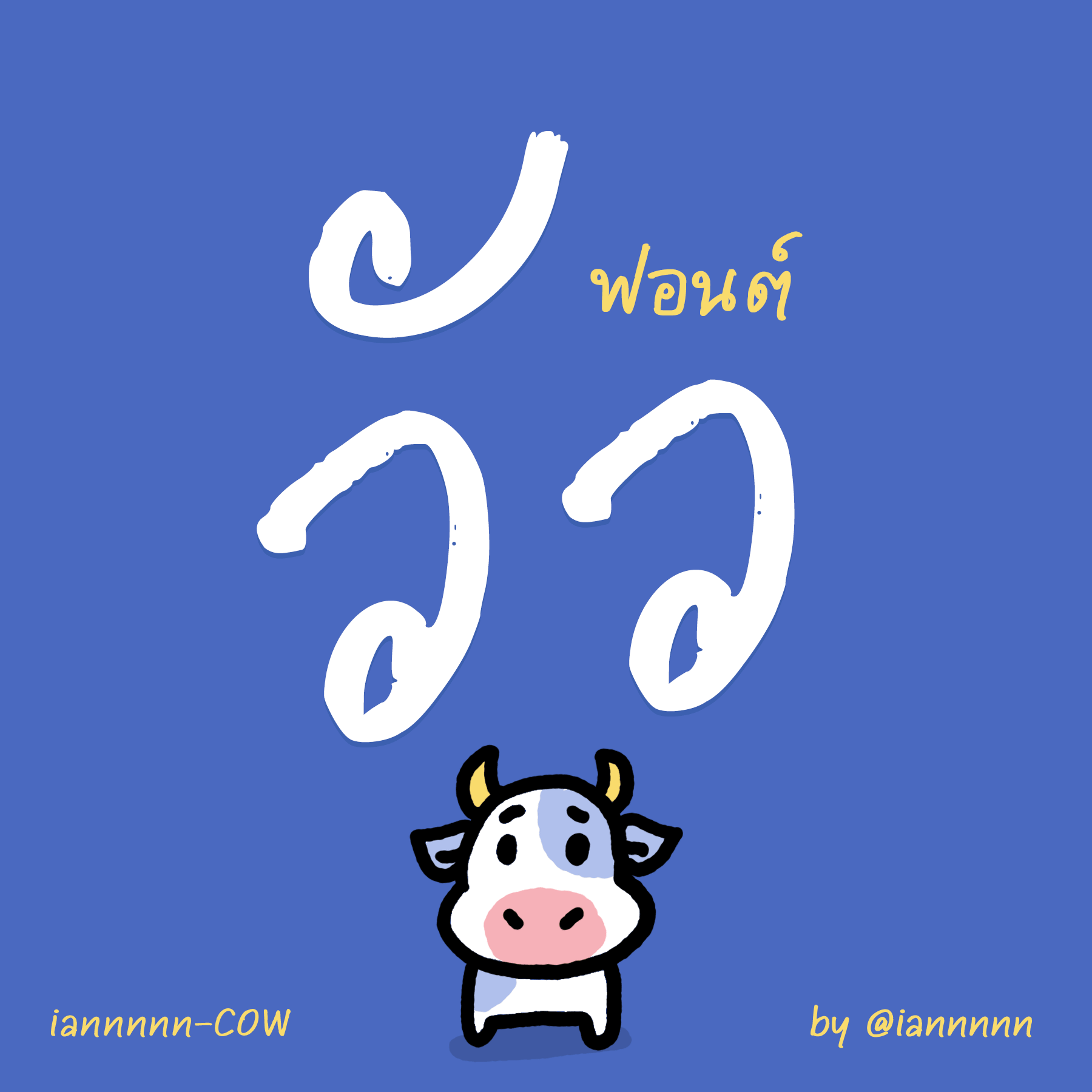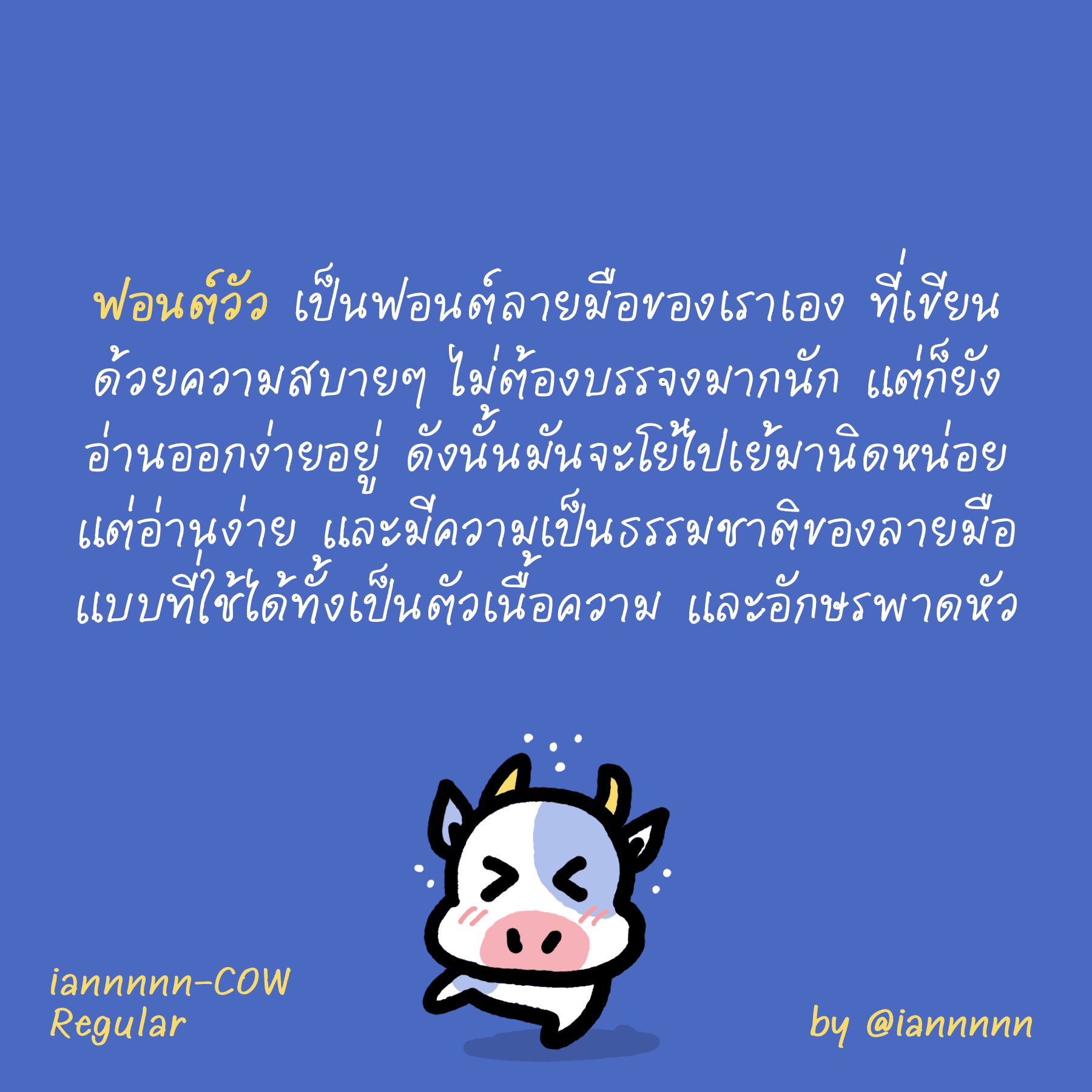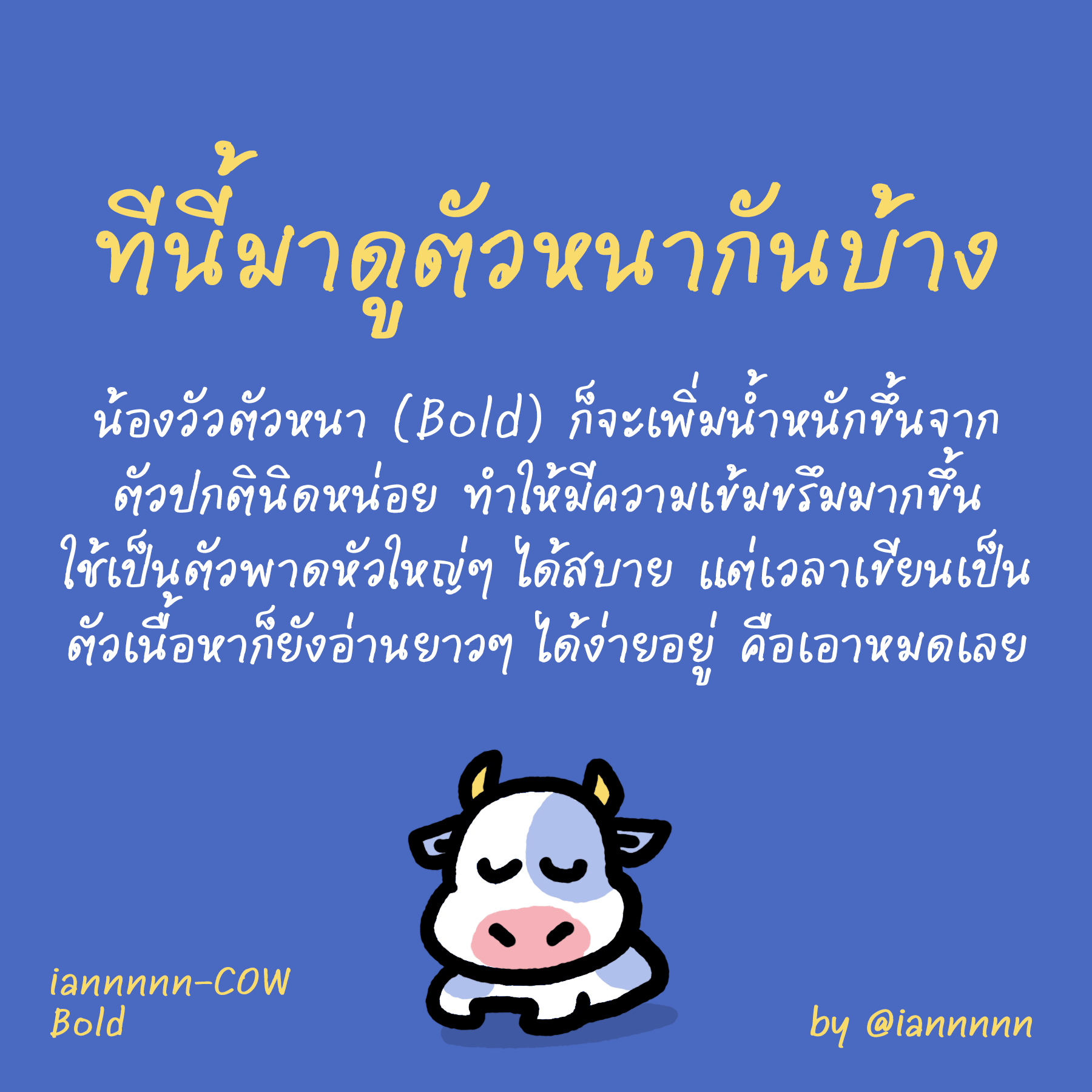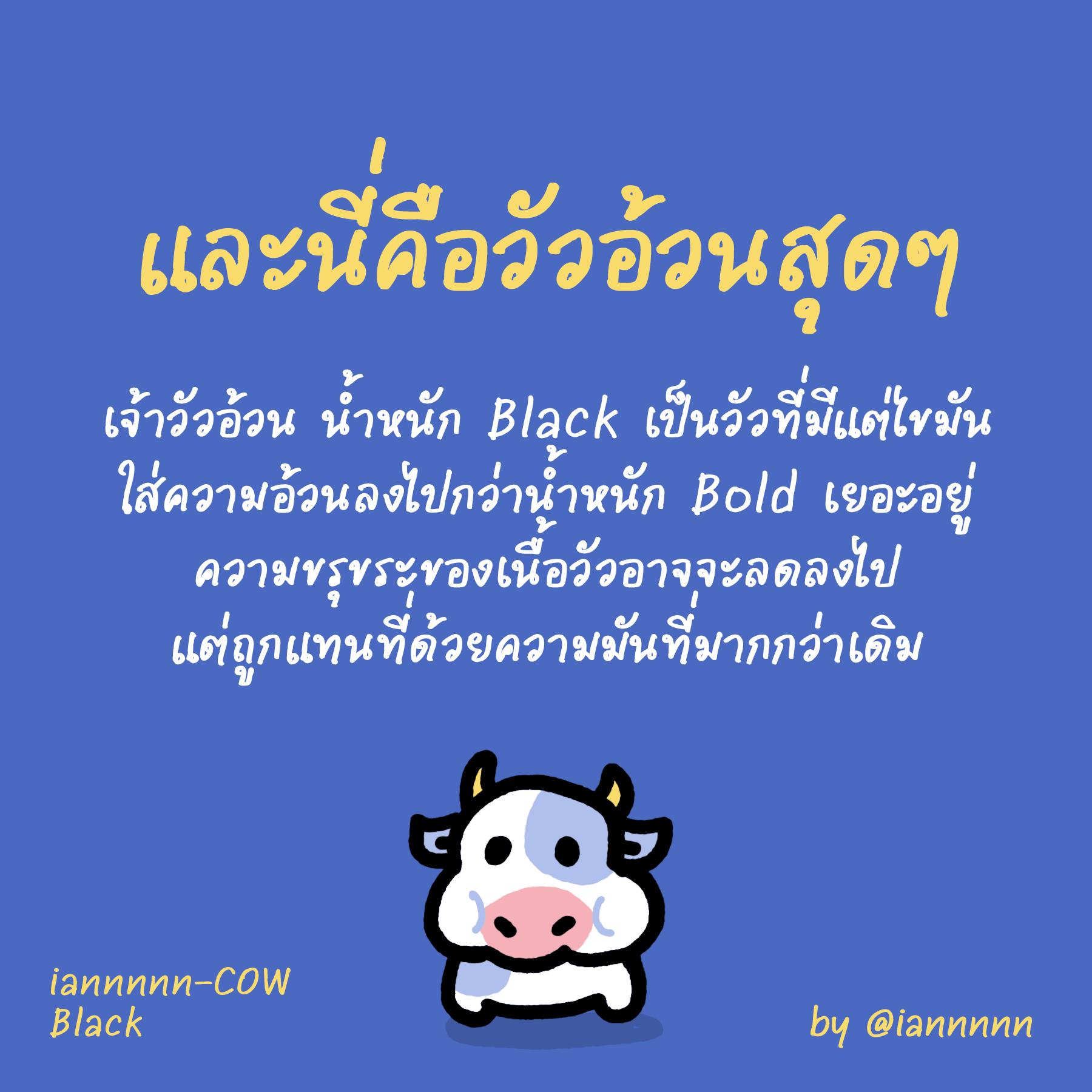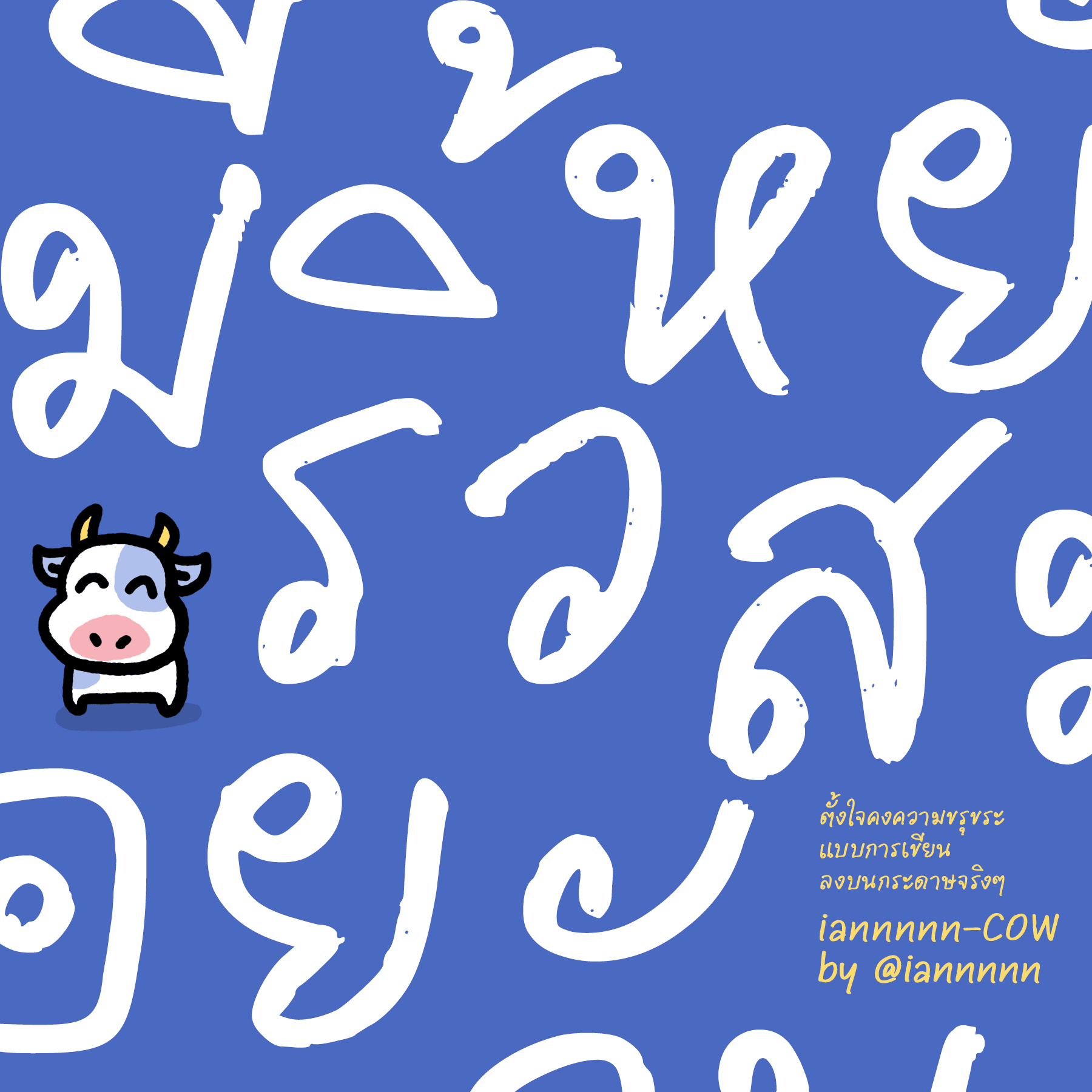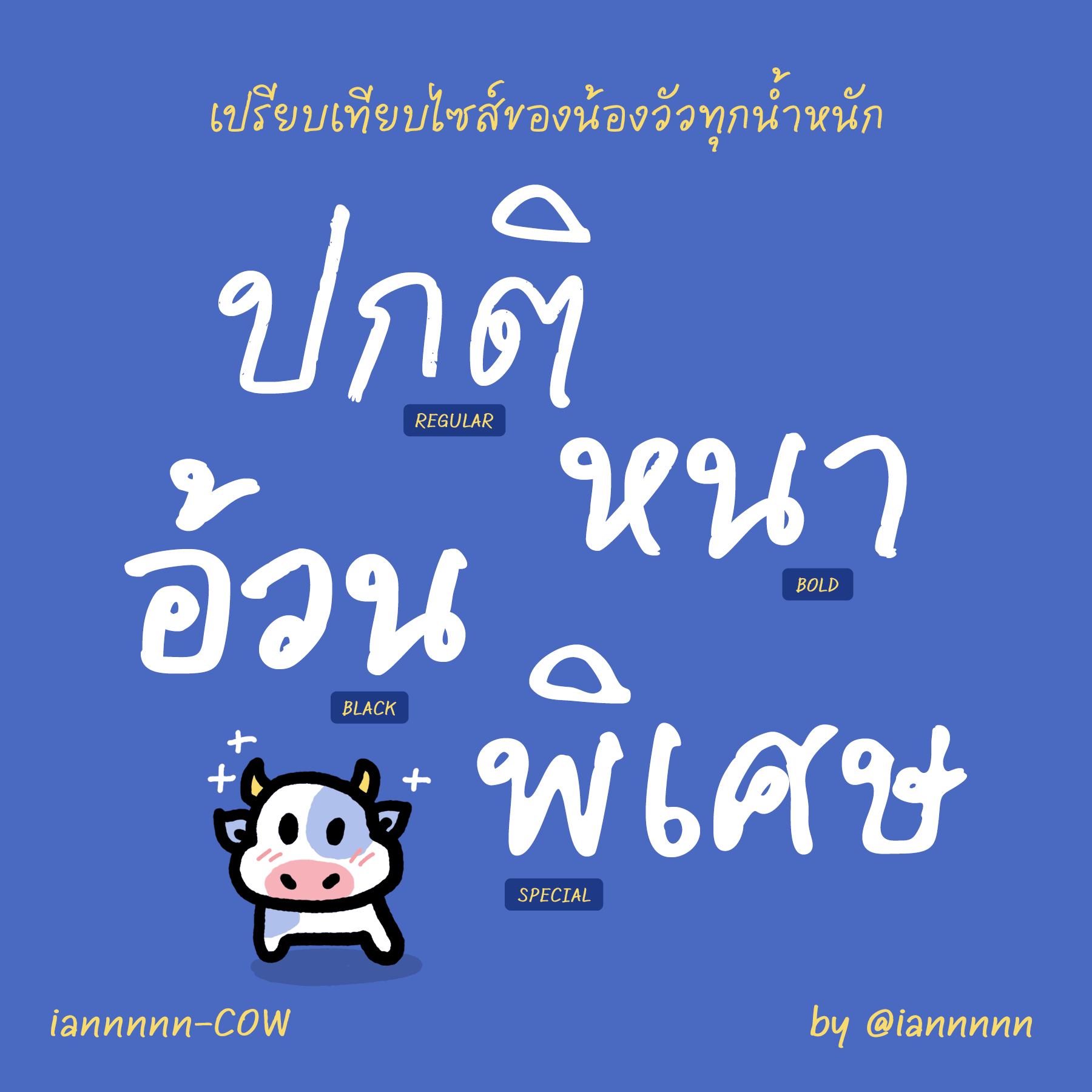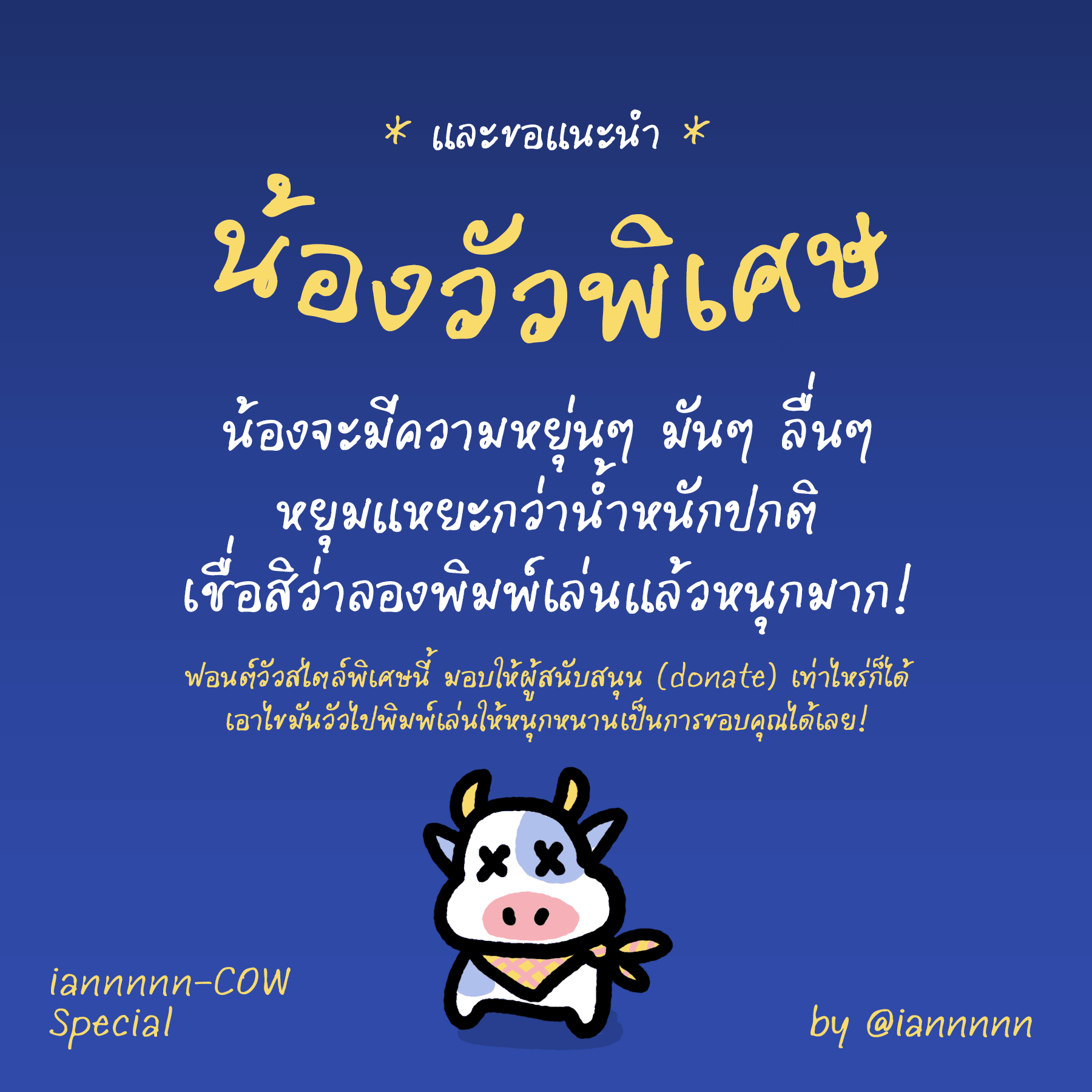
วัว (iannnnn-COW)
ฟอนต์ลายมือเจ้าเดียวกับฟอนต์หมา แต่มีความซน วุ่นวาย ไม่เรียบร้อยนัก แต่ก็ยังอ่านง่ายเป็นธรรมชาติ มีรอยหยักเบาๆ เหมือนเขียนลงกระดาษจริง พร้อมสไตล์พิเศษ สำหรับผู้ donate เท่าไหร่ก็ได้จ้า
นี่เป็นลายมือของผมเองในอีกสไตล์นึง เป็นลายมือที่ไม่ได้ตั้งใจบรรจงเท่าไหร่ เวลาเขียนรีบๆ ก็จะได้ประมาณนี้ครับ
เมื่อเทียบกับฟอนต์หมา ตัวนั้นจะมีความเรียบร้อยน่ารัก เป็นเด็กผู้หญิงกว่า และถ้าเทียบกับฟอนต์ลิง ตัวนั้นก็จะเขียนรีบๆ เหมือนกัน แต่ไม่มีหัว ดังนั้นฟอนต์วัวก็จะอยู่ระหว่างกลางของสองฟอนต์ที่ว่า
โดยมีคุณสมบัติหลักคือ แม้จะเป็นฟอนต์ลายมือที่ไม่เนี้ยบ แต่ก็ยังอ่านง่าย สามารถใช้ในกับงานเนื้อหา ที่พิมพ์ยาวๆ แต่ยังคงอ่านแล้วไหลลื่นพอสมควร
เบื้องหลังการออกแบบ : วัว (iannnnn-COW)
ฟอนต์วัว (iannnnn-COW)